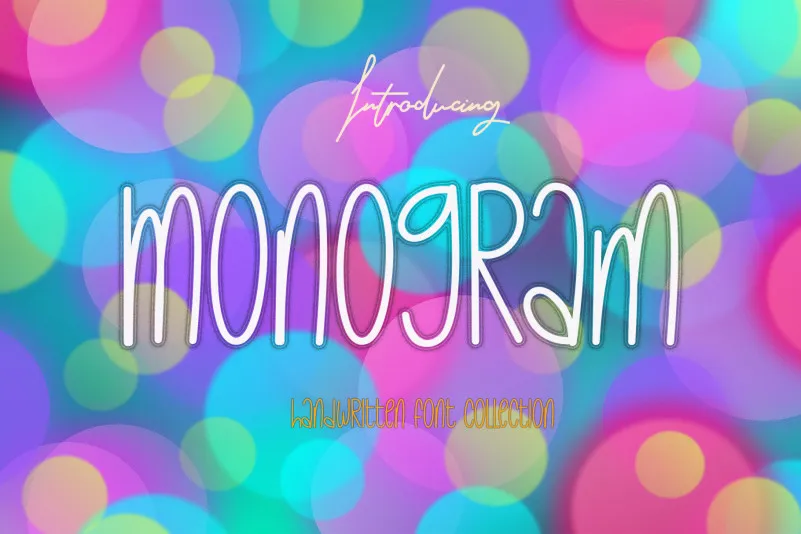
Esta é uma fonte manuscrita leve e versátil que se destaca em todas as aplicações. Ela transmite uma sensação quente, descontraída e alegre, tornando cada ideia de projeto em verdadeiras obras de arte. Com essa fonte encantadora, você pode explorar suas infinitas variações. Experimente-a e transforme seus projetos digitais em realidade visualmente impactantes. Monogram é uma opção perfeita para designers que buscam personalidade e flexibilidade em seu trabalho gráfico.